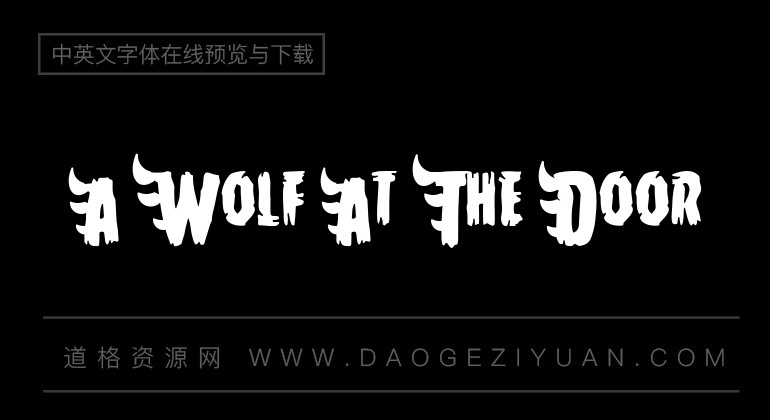
A Wolf At The Door
A Wolf At The Door 是一款由葡萄牙独立游戏开发者 Polygon Treehouse 制作的恐怖游戏。游戏中玩家将扮演一个陷入危险境地的女孩,她必须面对可怕的野兽,并试图从它的魔掌中逃脱。游戏的画面以黑白色调为主,并且以抽象的画面表现出恐惧的氛围,游戏的字体也与此相符,使用了一种粗犷的字体,表达出恐惧的气息。
A Wolf At The Door是一款非常不错的手写艺术字体,具有很好的视觉感,适合于文化类的宣传设计、商业类品牌的广告和产品包装设计以及个性化文字排版等较多场景。